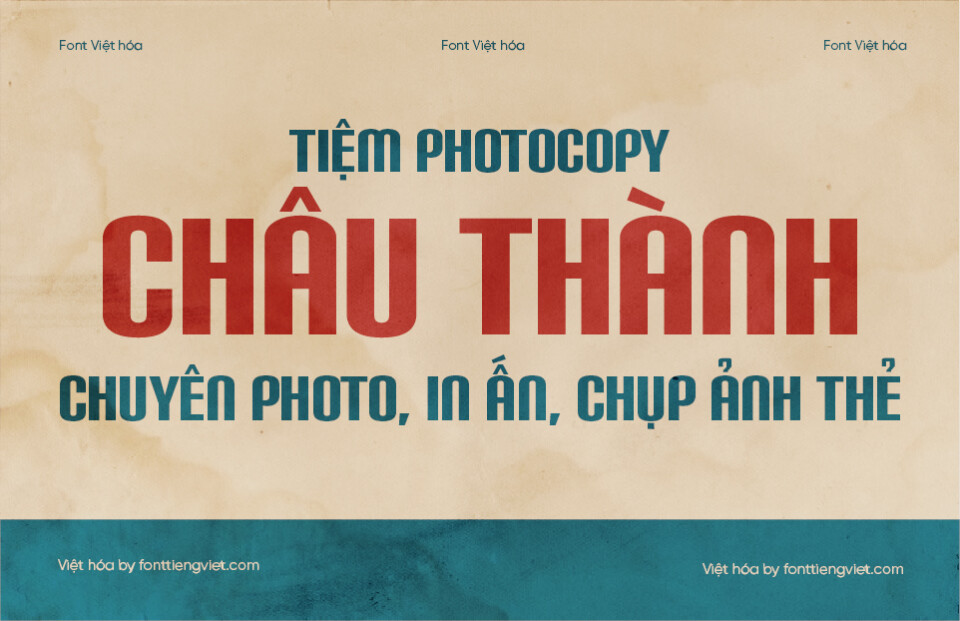
Giới thiệu về Font Việt hóa 1FTV VIP Carbon
Trong thế giới thiết kế hiện đại, việc lựa chọn một Font Chữ phù hợp đóng vai trò quyết định đến tính thẩm mỹ và thông điệp của sản phẩm. Font Việt hóa 1FTV VIP Carbon là một trong những bộ phông chữ độc đáo, mang phong cách mạnh mẽ, hiện đại và vô cùng chuyên nghiệp. Được tinh chỉnh kỹ lưỡng để hỗ trợ đầy đủ tiếng Việt, bộ font này giúp các nhà thiết kế loại bỏ hoàn toàn lỗi hiển thị dấu, mang lại sự mượt mà tối đa trên mọi nền tảng kỹ thuật số.
Đặc điểm nổi bật của phông chữ
Sự khác biệt của Font Việt hóa 1FTV VIP Carbon nằm ở cấu trúc hình khối chắc chắn kết hợp với các đường nét bo góc tinh tế. Kiểu dáng này gợi liên tưởng đến sự bền bỉ của sợi carbon và công nghệ tương lai. Đây là lựa chọn lý tưởng cho các dự án thiết kế logo, bao bì sản phẩm công nghệ, hoặc các ấn phẩm truyền thông đòi hỏi sự đột phá và nam tính.
Ứng dụng thực tế của Font Việt hóa 1FTV VIP Carbon
Bộ font này không chỉ giới hạn trong giới đồ họa chuyên nghiệp mà còn rất phù hợp cho học sinh, sinh viên làm slide thuyết trình hoặc trang trí báo tường điện tử. Nhờ tính năng dễ đọc và khả năng hiển thị sắc nét trên cả màn hình máy tính lẫn in ấn, 1FTV VIP Carbon giúp nội dung truyền tải trở nên cuốn hút và dễ tiếp cận hơn đối với người xem.
Lưu ý khi sử dụng trong trình bày
Khi áp dụng Font Việt hóa 1FTV VIP Carbon, bạn nên kết hợp với các tông màu trung tính như đen, xám hoặc xanh đậm để làm nổi bật tinh thần công nghệ. Việc điều chỉnh khoảng cách giữa các chữ cái (kerning) cũng sẽ giúp tiêu đề của bạn trở nên cân đối và bắt mắt hơn rất nhiều.
Kết luận về bộ phông chữ 1FTV VIP Carbon